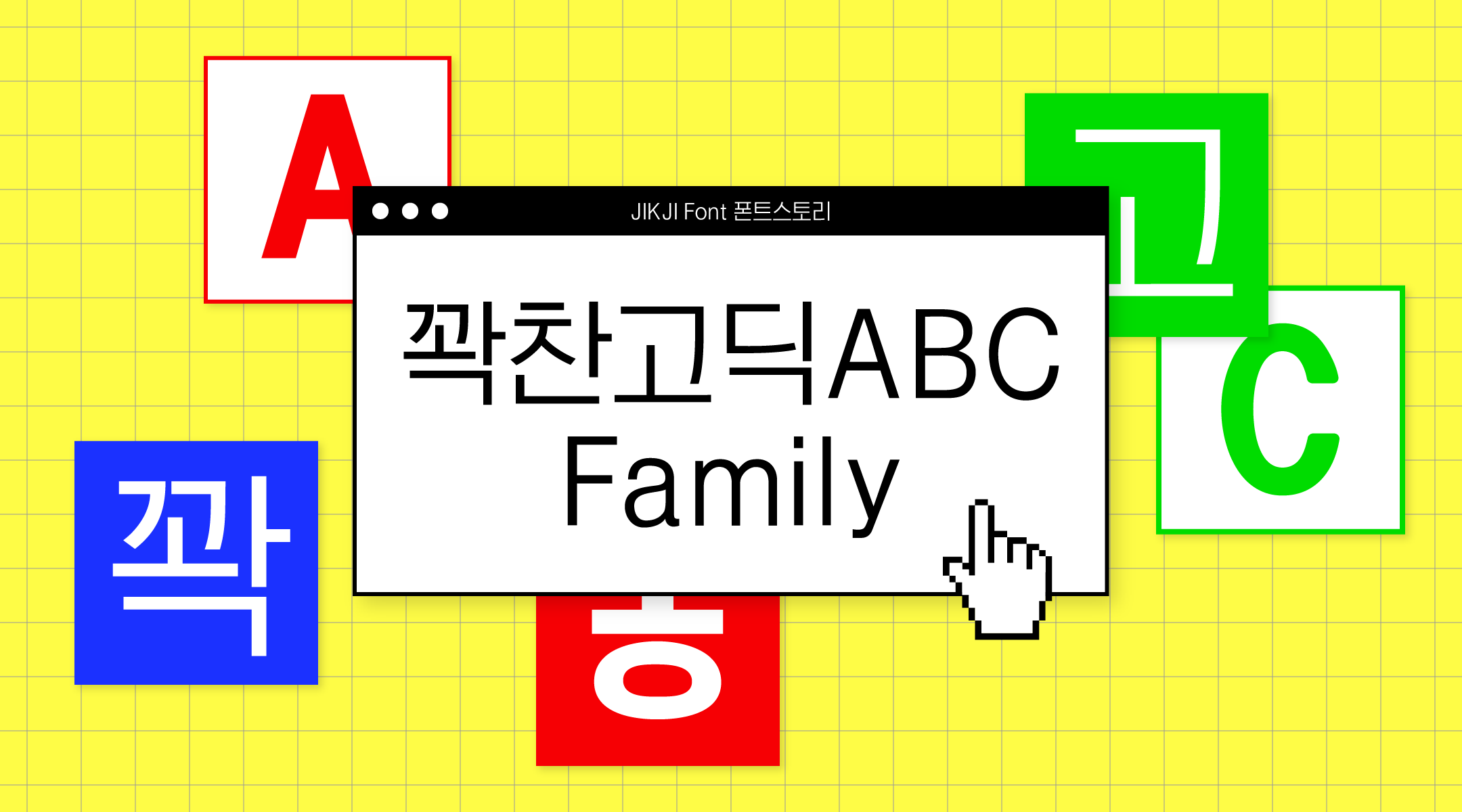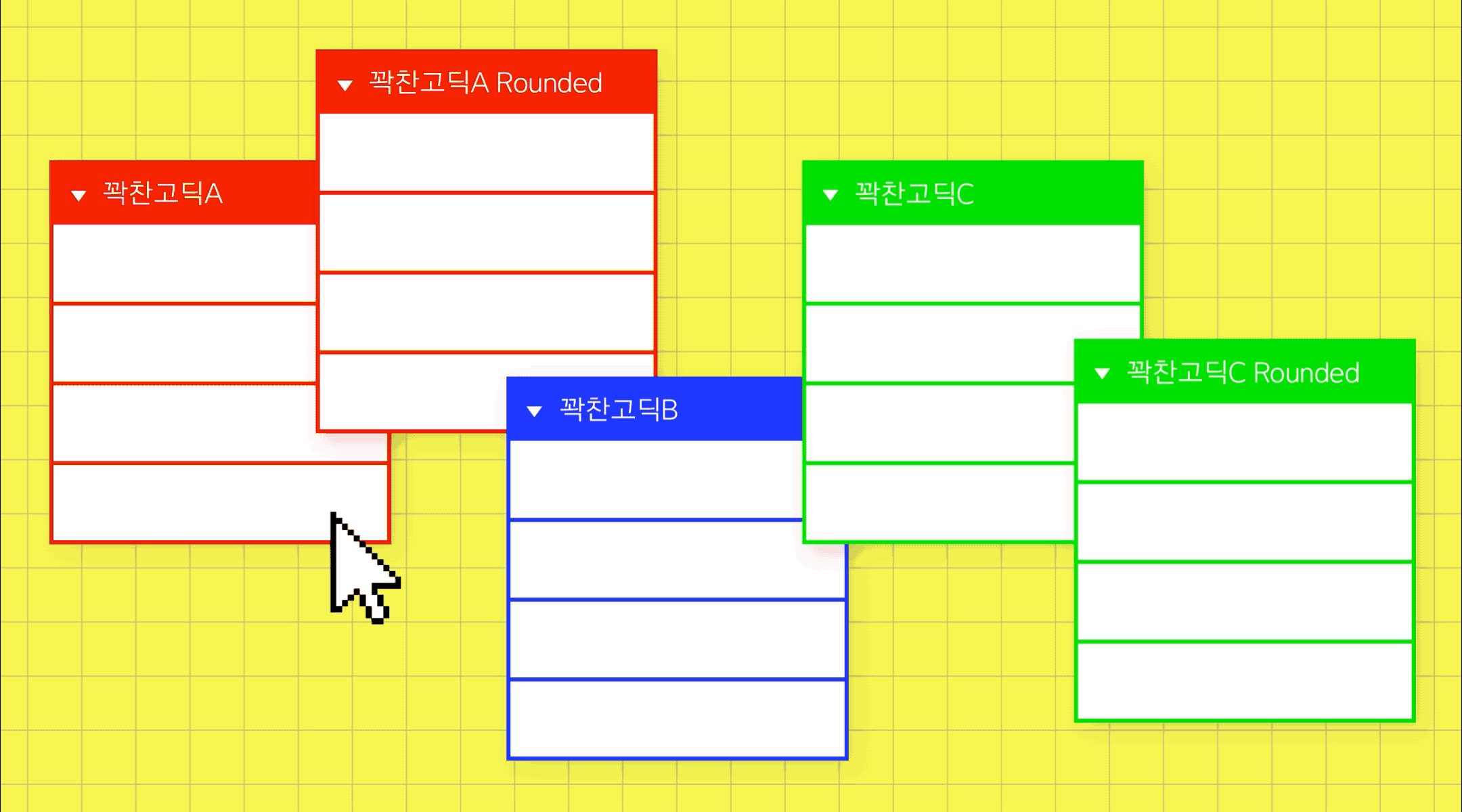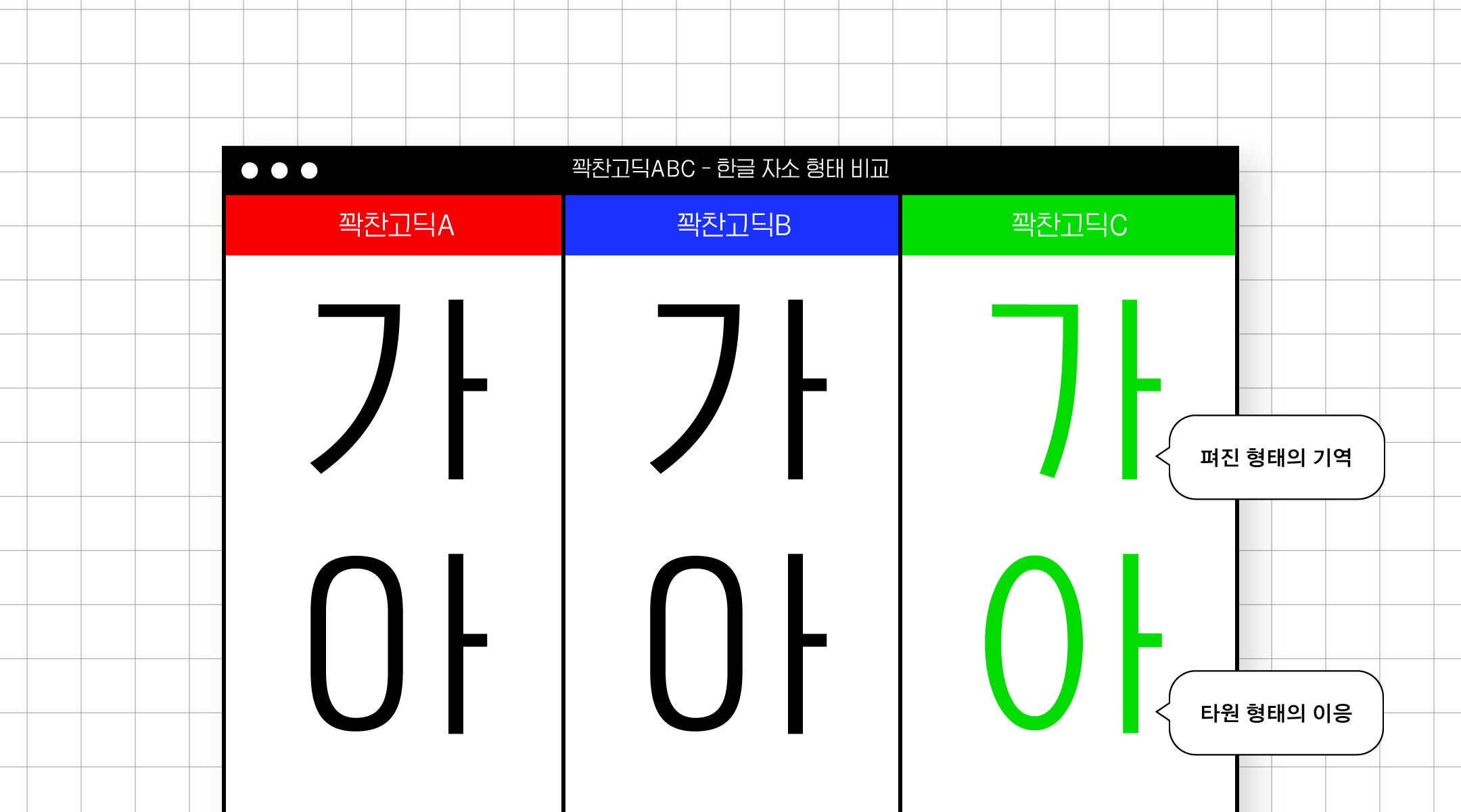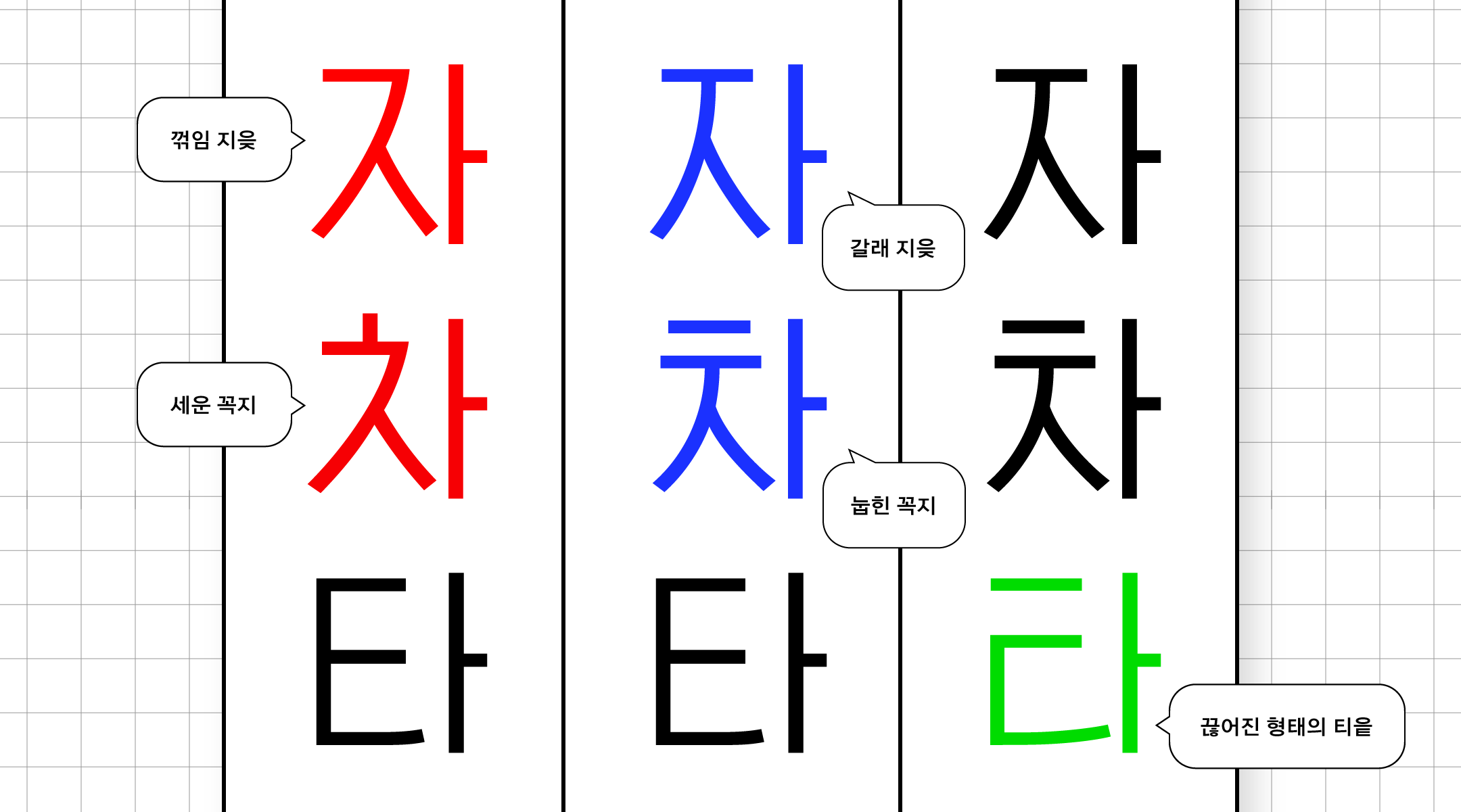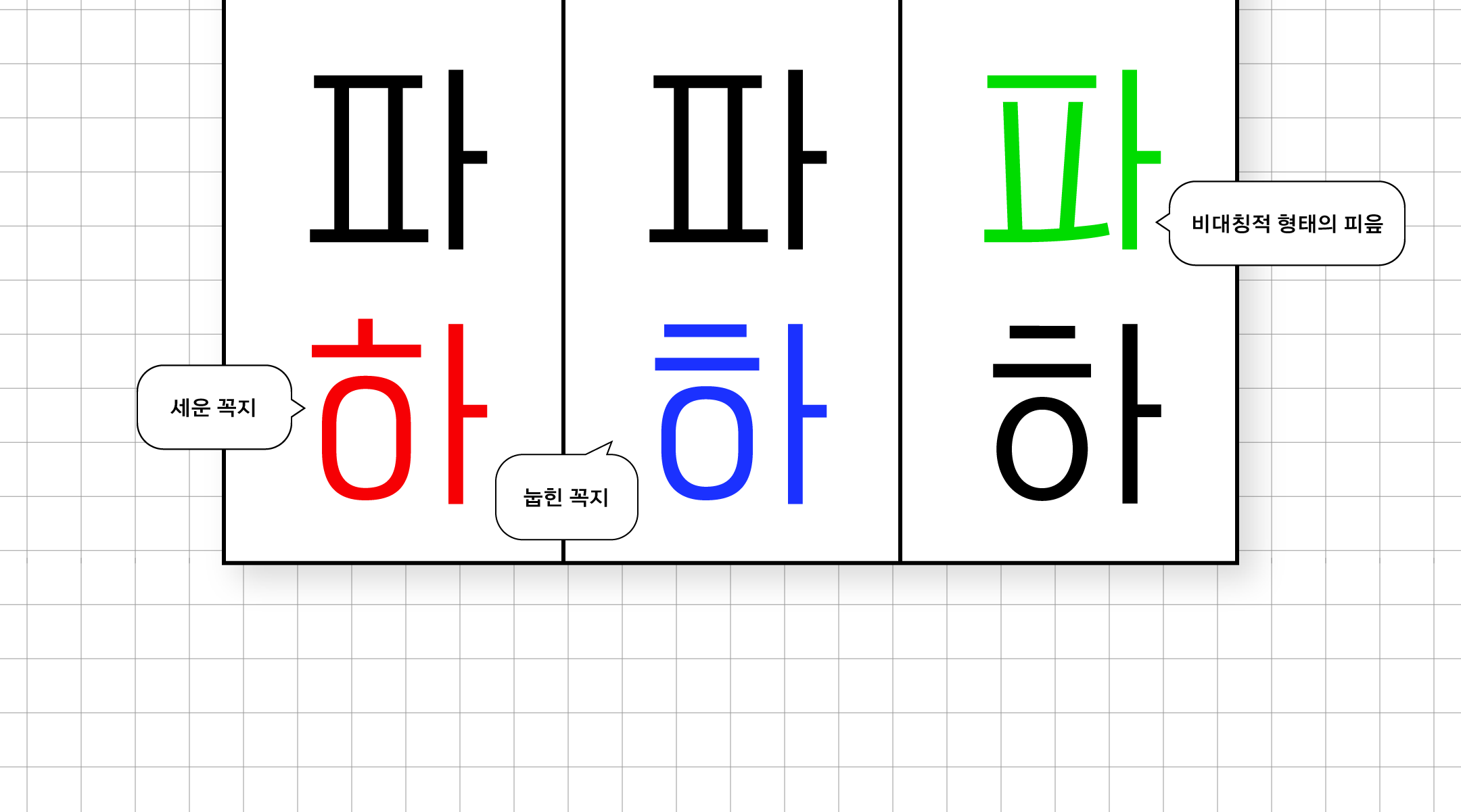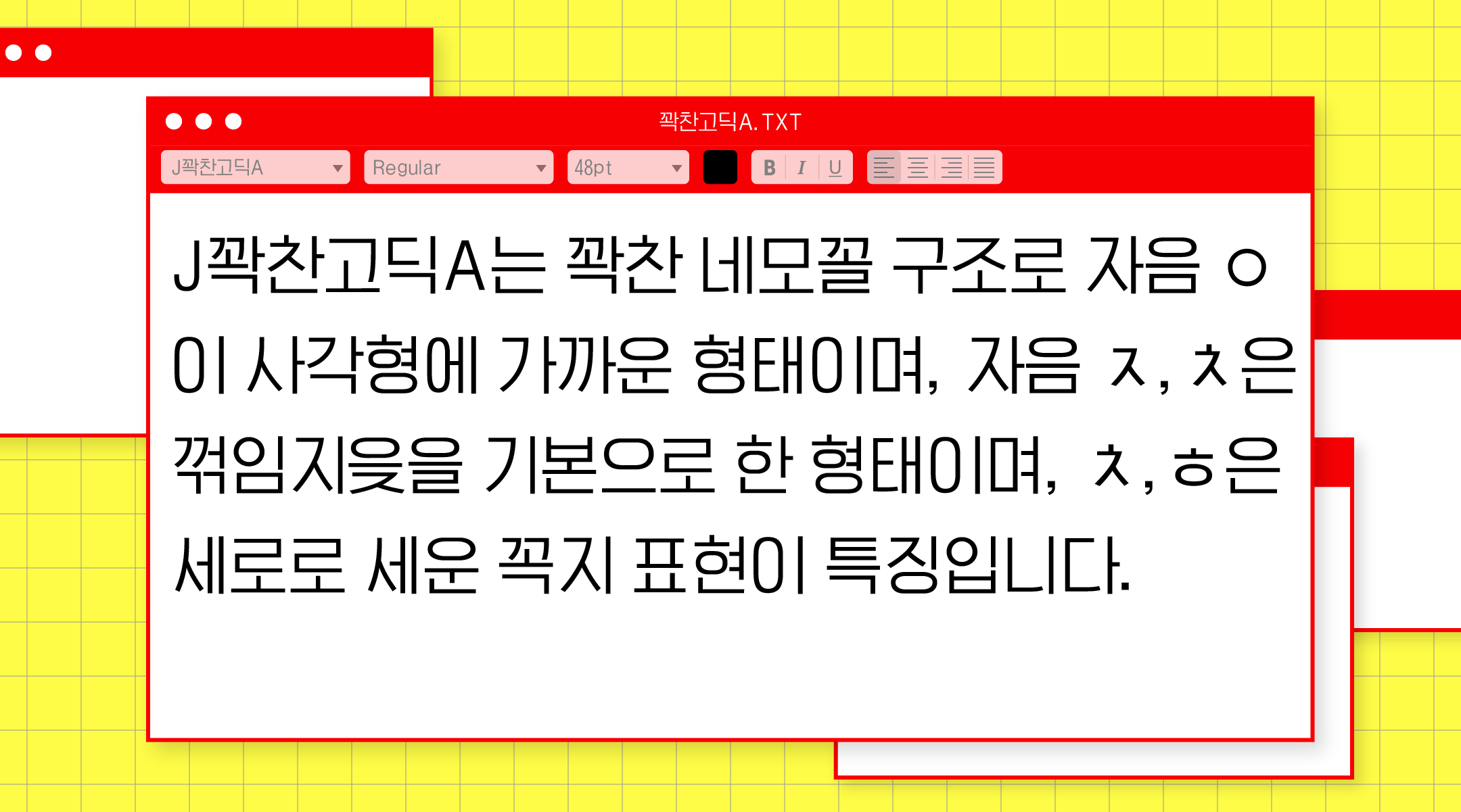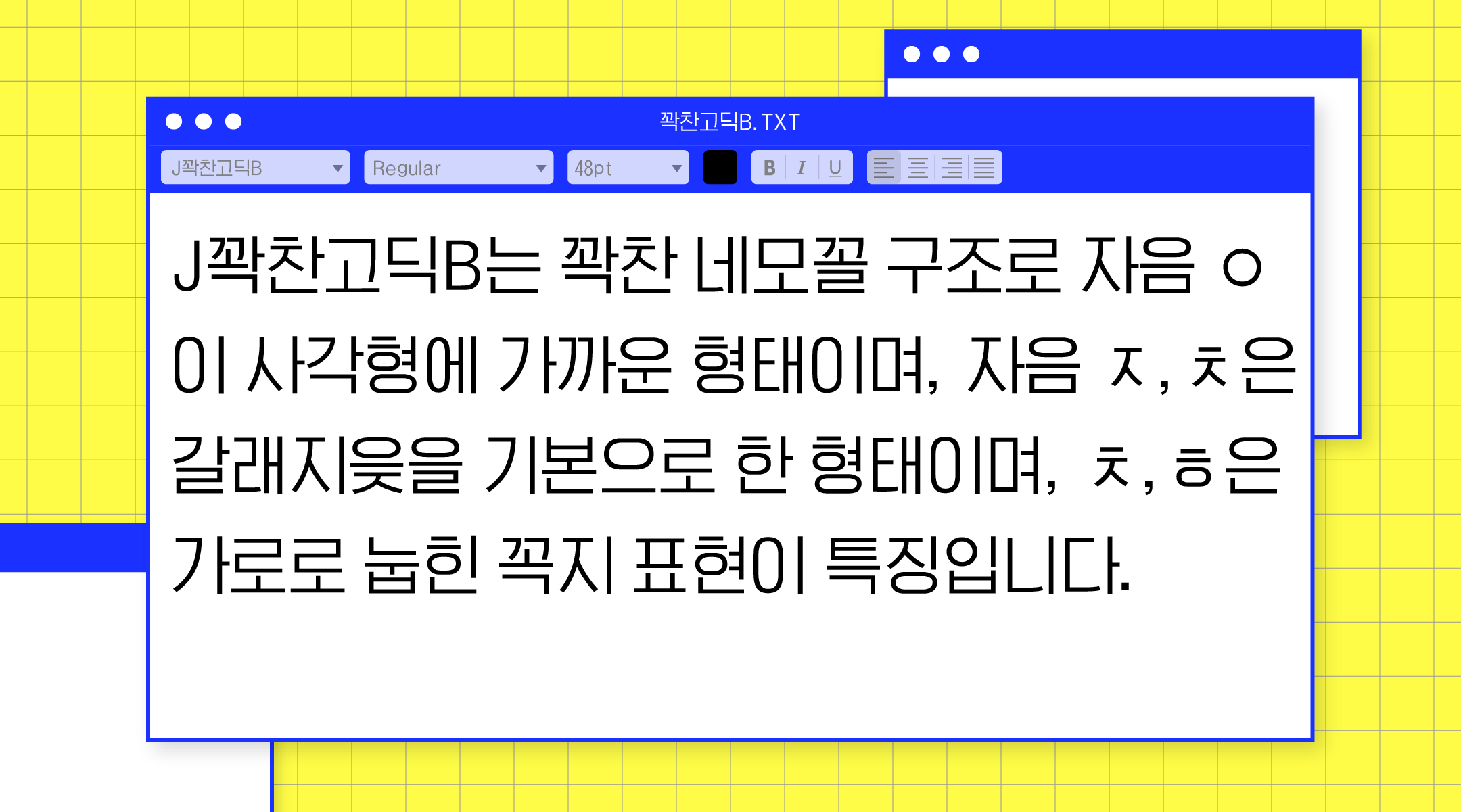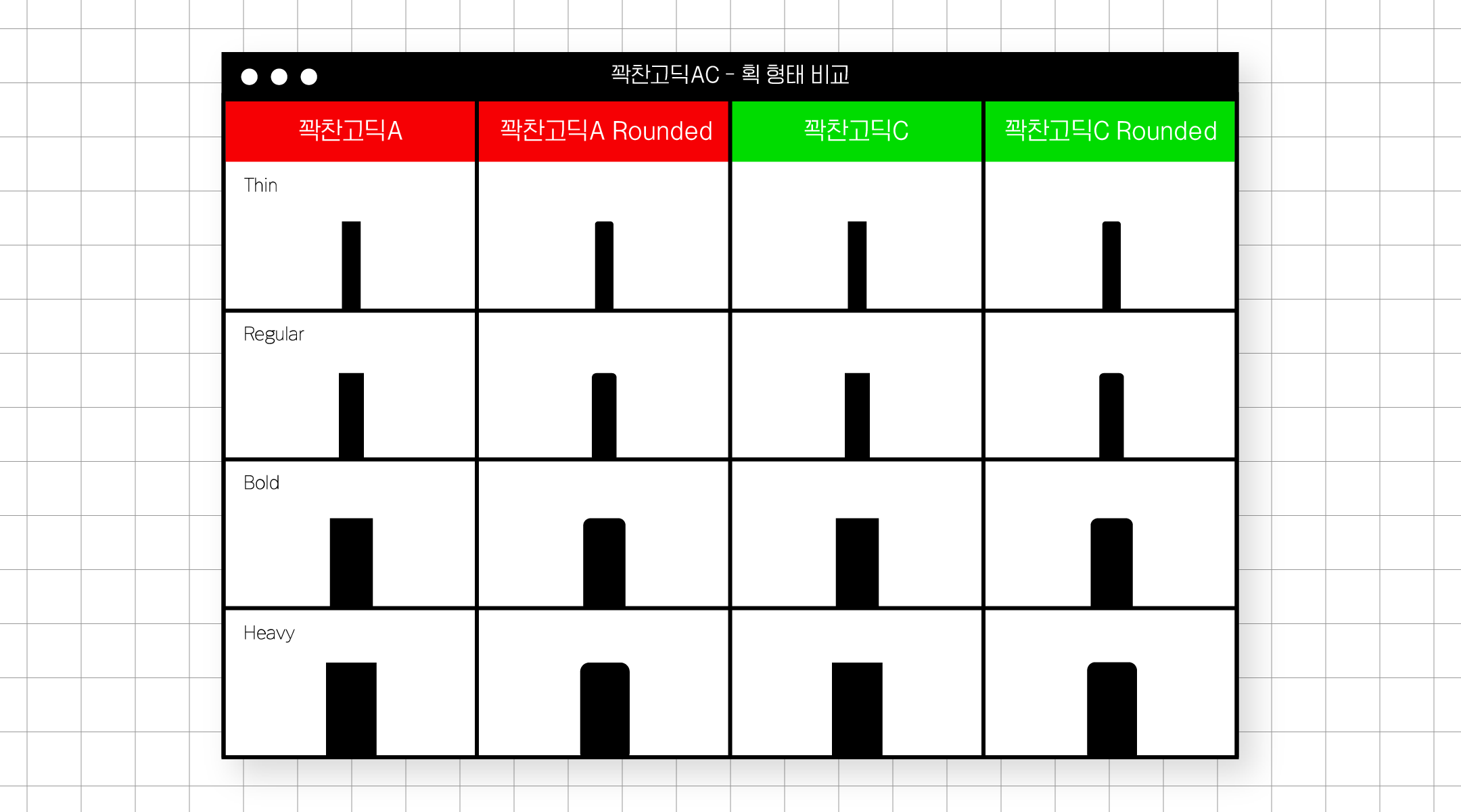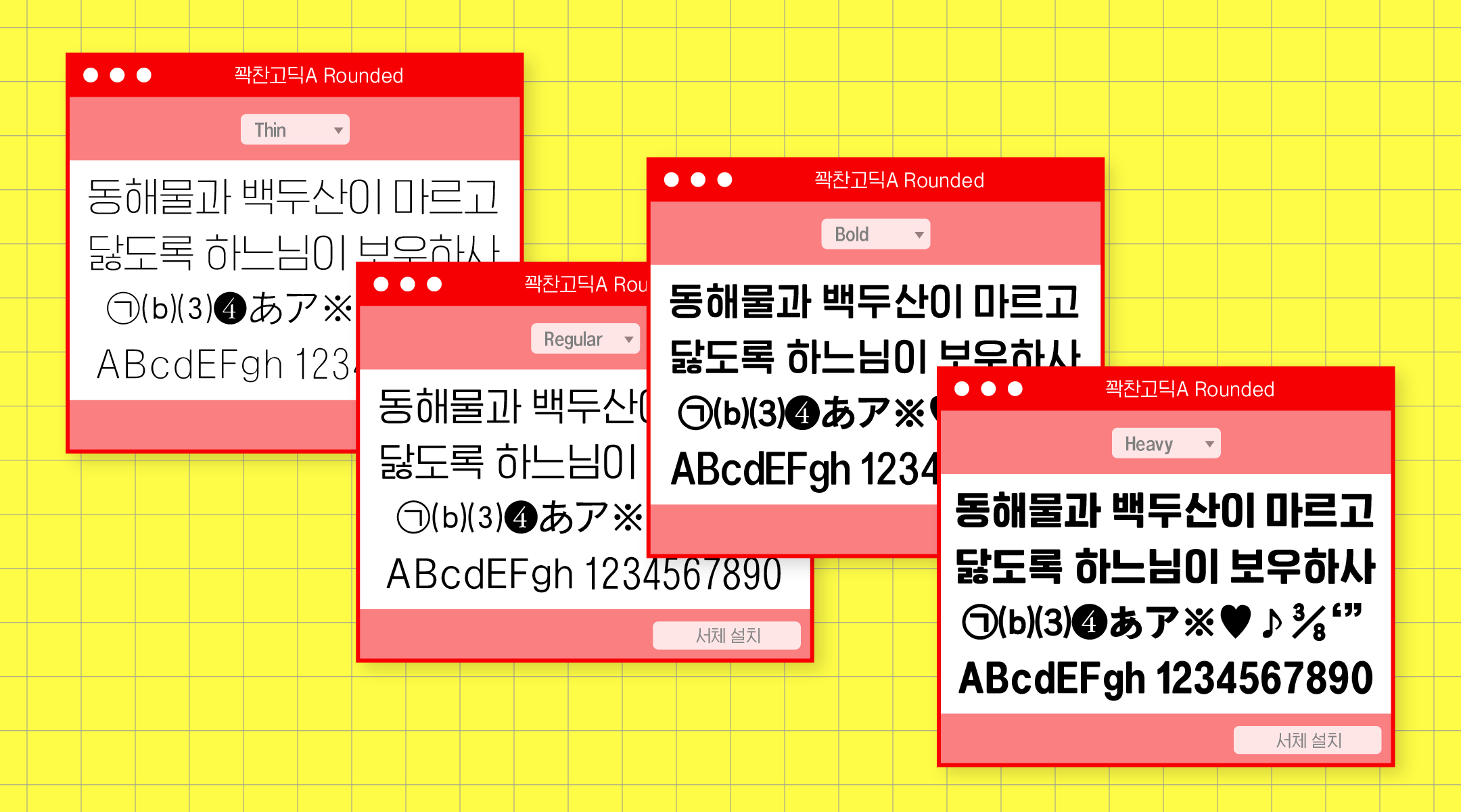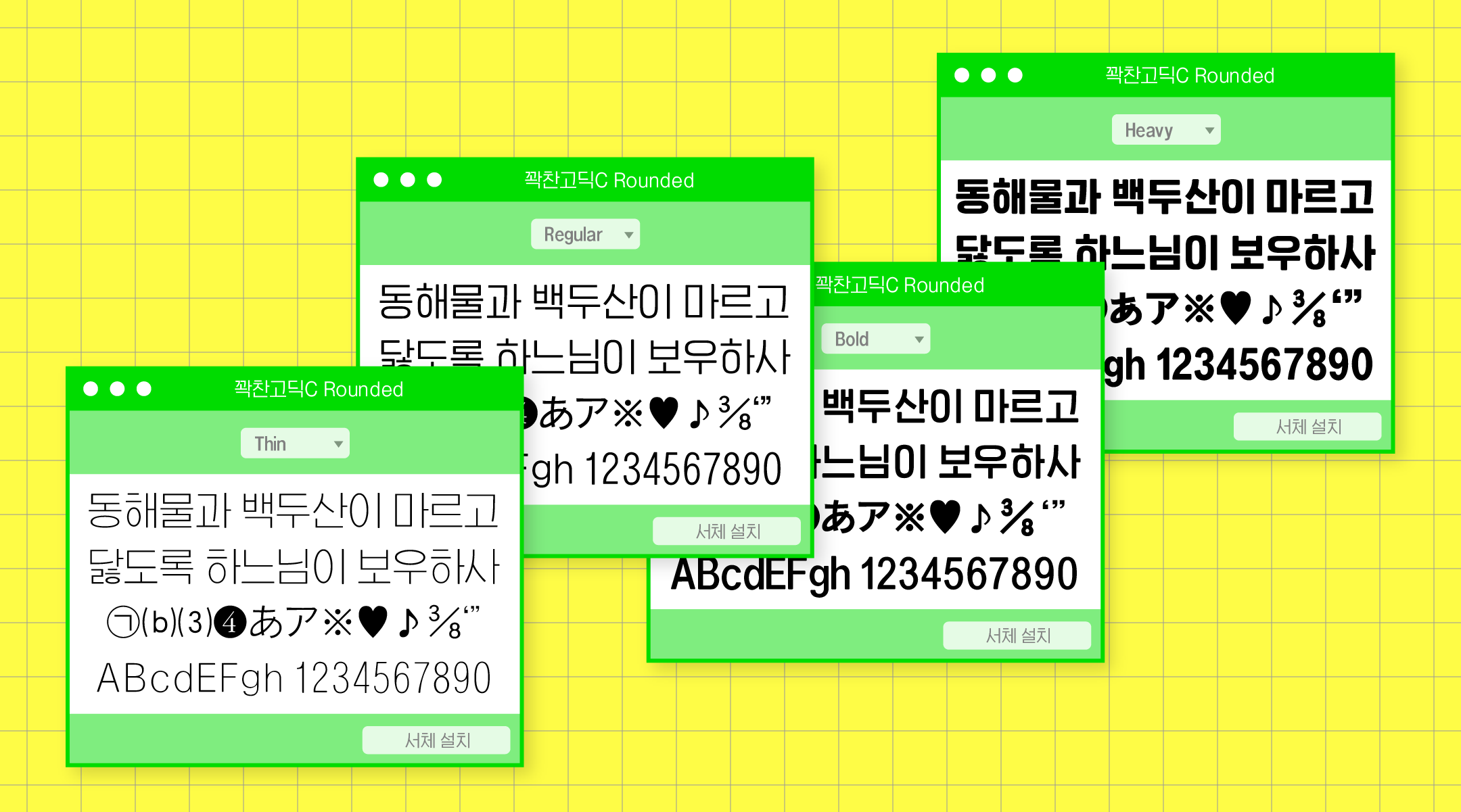
J꽉찬고딕A는 직지소프트의 직지그래픽 폰트입니다. 출시일은 2020.01.01입니다. 4종으로 구성되어 있습니다.
다양한 컨셉으로 활용이 가능하고 독특한 디자인 요소가 많은 서체 시리즈. 개성있는 디테일로 시각적 재미를 더하고 풍부한 이야기를 담을 수 있는 서체이다.
J꽉찬고딕은 소비자의 요구에 맞춰 명쾌하고 효율적인 시각적 전달에 중점을 두고 기획된 폰트입니다. J직지고딕의 손맛과 인간미가 느껴지는 'ㅅ'꼴 디자인을 계승하면서 꽉 찬 네모꼴 스타일로 디자인한 폰트입니다. 2020년 출시된 J꽉찬고딕A, B를 시작으로 2021년에는 J꽉찬고딕C와 Rounded가 추가되어 총 20종의 패밀리로 확장되었습니다. J꽉찬고딕A는 꽉찬 네모꼴 구조에 ‘ㅈ’, ‘ㅊ’을 꺾임 지읒 형태이고, ‘ㅊ’, ‘ㅎ’의 꼭지는 세로로 세운 것이 특징입니다. J꽉찬고딕B는 동일한 구조 안에서 ‘ㅈ’, ‘ㅊ’을 갈래 지읒 형태, ‘ㅊ’, ‘ㅎ’은 가로로 눕힌 꼭지 표현으로 차별화하였으며 'ㅇ'은 사각형에 가까운 꽉찬 형태입니다. J꽉찬고딕C는 'ㅇ'을 타원형 구조로 디자인하고 'ㄱ','ㅌ' 등 일부 자형의 끝 모양을 휘어지거나 획을 생략하여 상쾌한 경량감을 주었습니다. J꽉찬고딕 Rounded는 J꽉찬고딕을 바탕으로 모든 글자의 끝맺음의 모서리 부분만 섬세하게 조정된 굴림형태입니다. 단단한 고딕의 인상을 유지하면서도 세밀한 부드러움을 더했습니다. J꽉찬고딕 패밀리는 사용자 선택의 폭을 넓혀 어느 곳에 사용해도 잘 융화되는 중립적인 고딕 서체입니다. 상업적 광고와 아이덴티티 등 주목도를 높이는데 유용하게 쓰일 뿐만 아니라 가독성이 중요한 편집물, 일반 문서 작업 등 다양한 분야에서 폭넓게 활용될 수 있습니다.